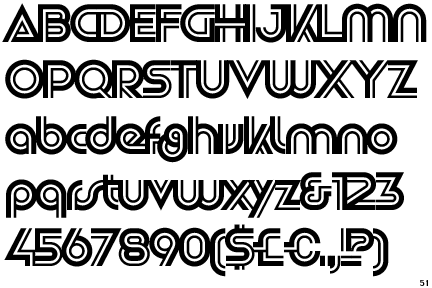
Chả là đang ngồi nghịch, tìm font đẹp, thấy cái font này ưng mà không biết tên nó là gì, lên What the font tìm thì nó không chính xác cho lắm,
anh chị em biết thì giúp mình với ạ:
Nhớ không nhầm thì font ày phải mua :v
Mình chỉ cần tìm cái tên thôi ạ, mua cũng được mà
Tên Font là j vậy b?
Planet Kosmos....em này free với mục đích cá nhân...inbox để nhận link tải...:)